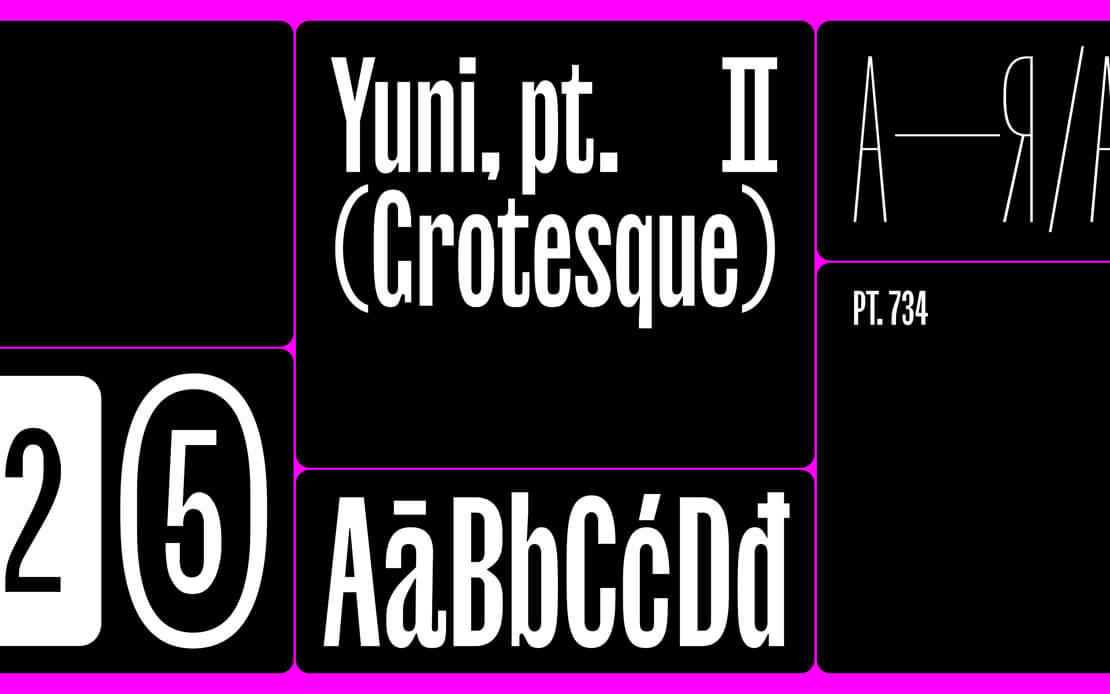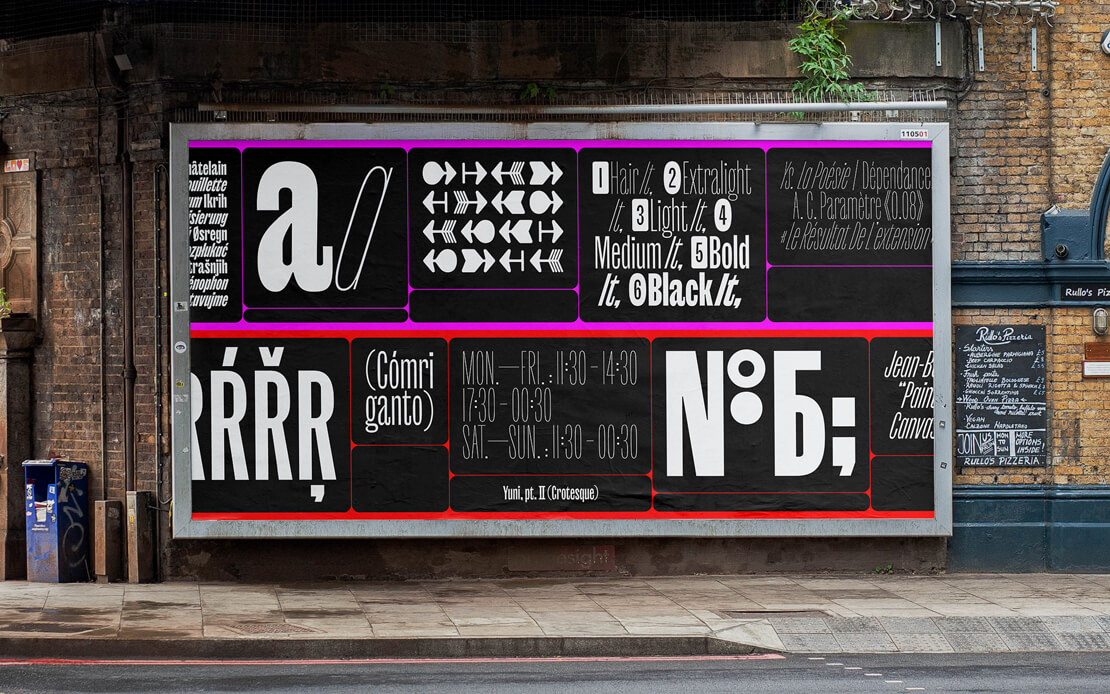
Yuni Grotesque: Schmale Sans mit Charakter
»Yuni Grotesque« ist die zweite Veröffentlichung innerhalb der Yuni-Kollektion von TypeMates. Die Schriftfamilie gibt sich schlank und verspielt.
Während sich die Punzen mit zunehmendem Gewicht zu nahezu kreisförmigen Innenräumen weiten, bleiben die Außenkonturen flach. So entsteht eine Kombination von Gegensätzen und eine spannungsvolle Mischung.
Flache Außenkonturen treffen auf weit gespannte, runde Innenräume. So entsteht ein eigenständiger Charakter mit subtilen Bezügen zur Schwesterfamilie Yuni Slab, jedoch klar positioniert als schmale Sans.
Schnitte und Zeichenumfang der »Yuni Grotesque«
Sechs Strichstärken von »Hair« bis »Black«, jeweils mit deutlich geneigten Kursiven (ca. 18°), ergeben zusammen 12 Schnitte. Zusätzlich steht eine Variable-Font-Version zur Verfügung, um Gewicht und Dynamik präzise zu steuern.
Pro Schnitt sind über 900 Glyphen enthalten. Der Ausbau umfasst muttersprachlich geprüftes Kyrillisch und unterstützt über 270 Sprachen. OpenType-Funktionen liefern darüber hinaus mehrere Ziffernsätze (inklusive eingekreister und eingerahmter Varianten), abgestimmte Pfeile sowie kontextabhängige Alternativen.